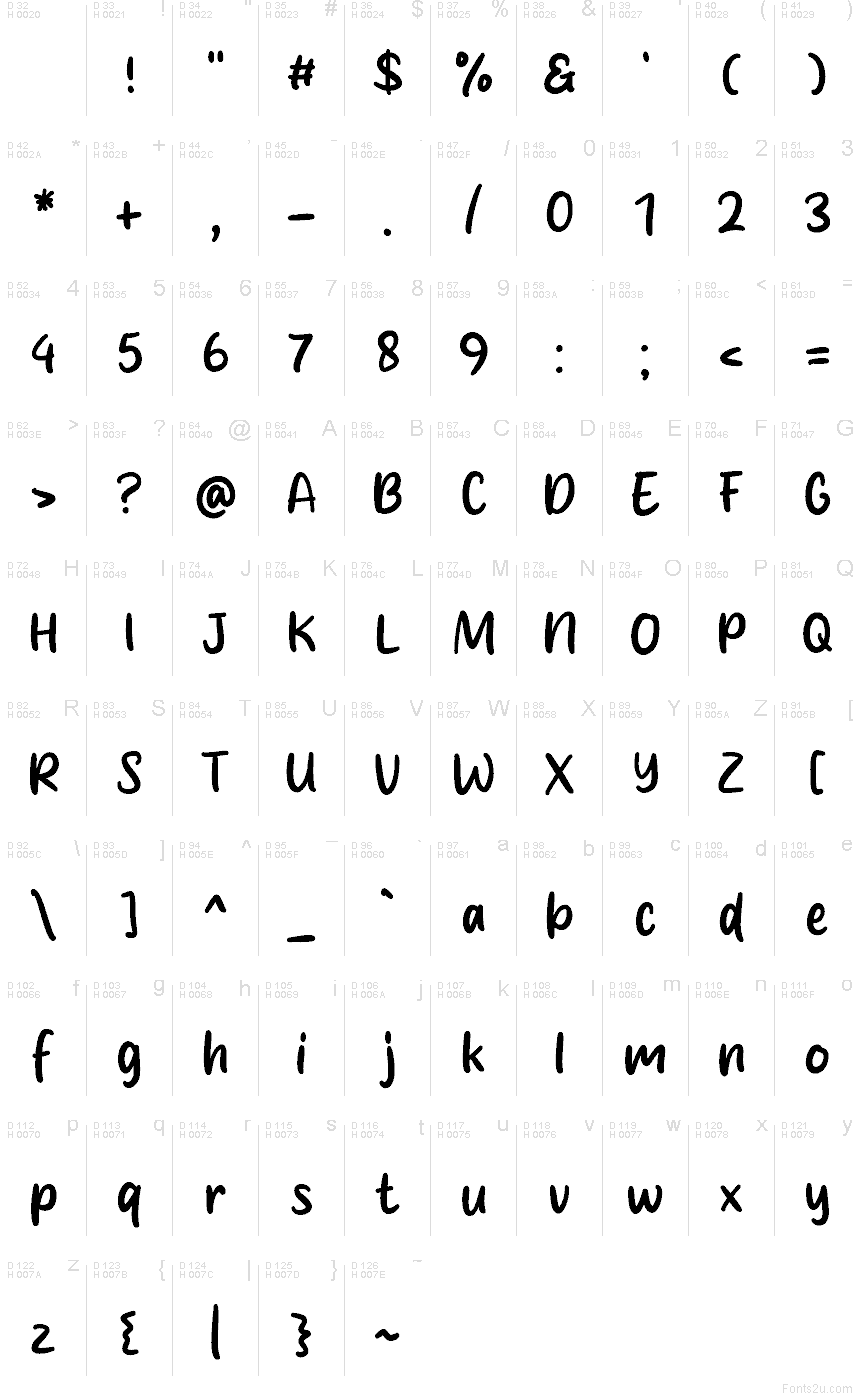
Créée en 2026 par MJType, Delight Burger est une police manuscrite gratuite aux lettres étirées et au tracé libre, affichant une allure entraînante et décontractée. Ses raccords arrondis, ses largeurs irrégulières et ses délicates variations d'épaisseur confèrent au lettrage la fluidité spontanée d'un tracé rapide au feutre.
Les marques alimentaires indépendantes et les entreprises familiales y trouveront un style adapté aux emballages et à la signalétique informelle. Ses formes vivantes conviennent également aux affiches d'événements. Dans l'édition, elle permet de faire des titres de livres de cuisine ou des pages d'activités pour enfants un véritable élément d'illustration.